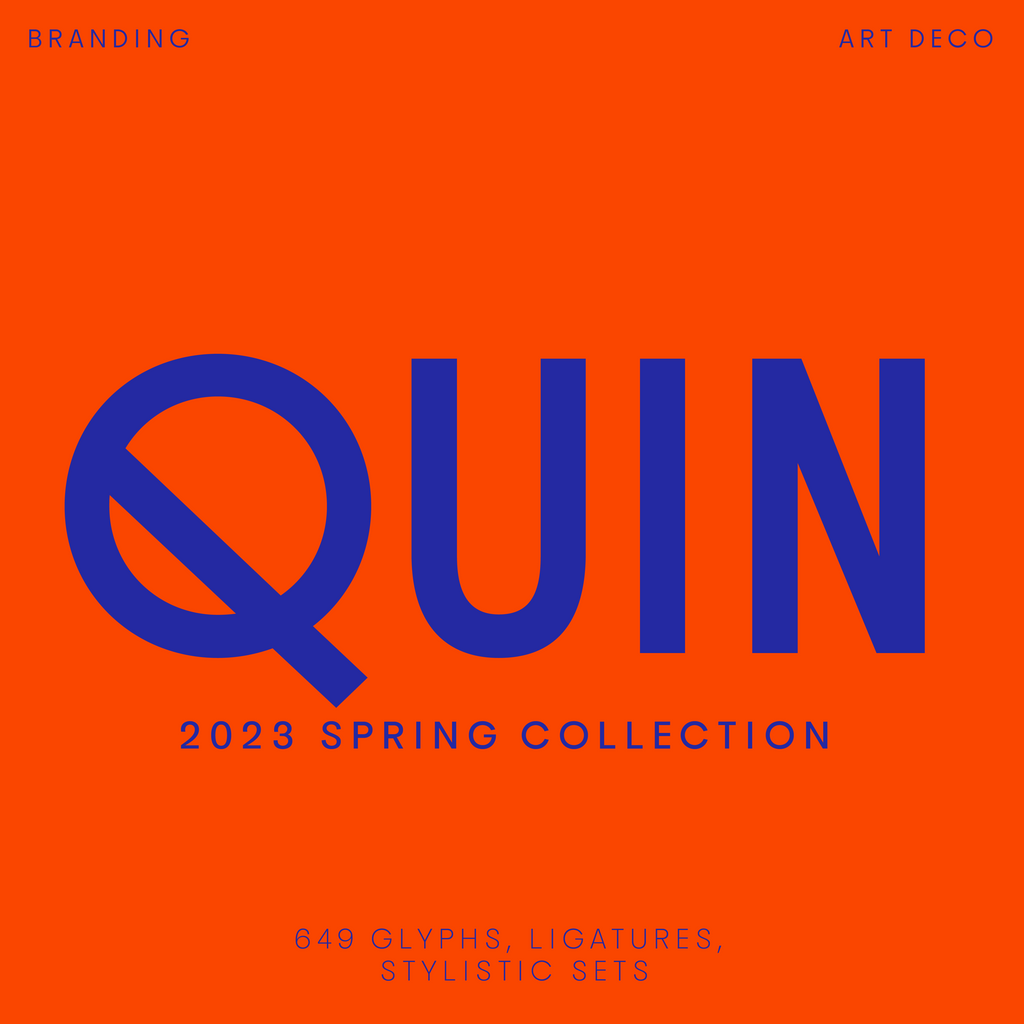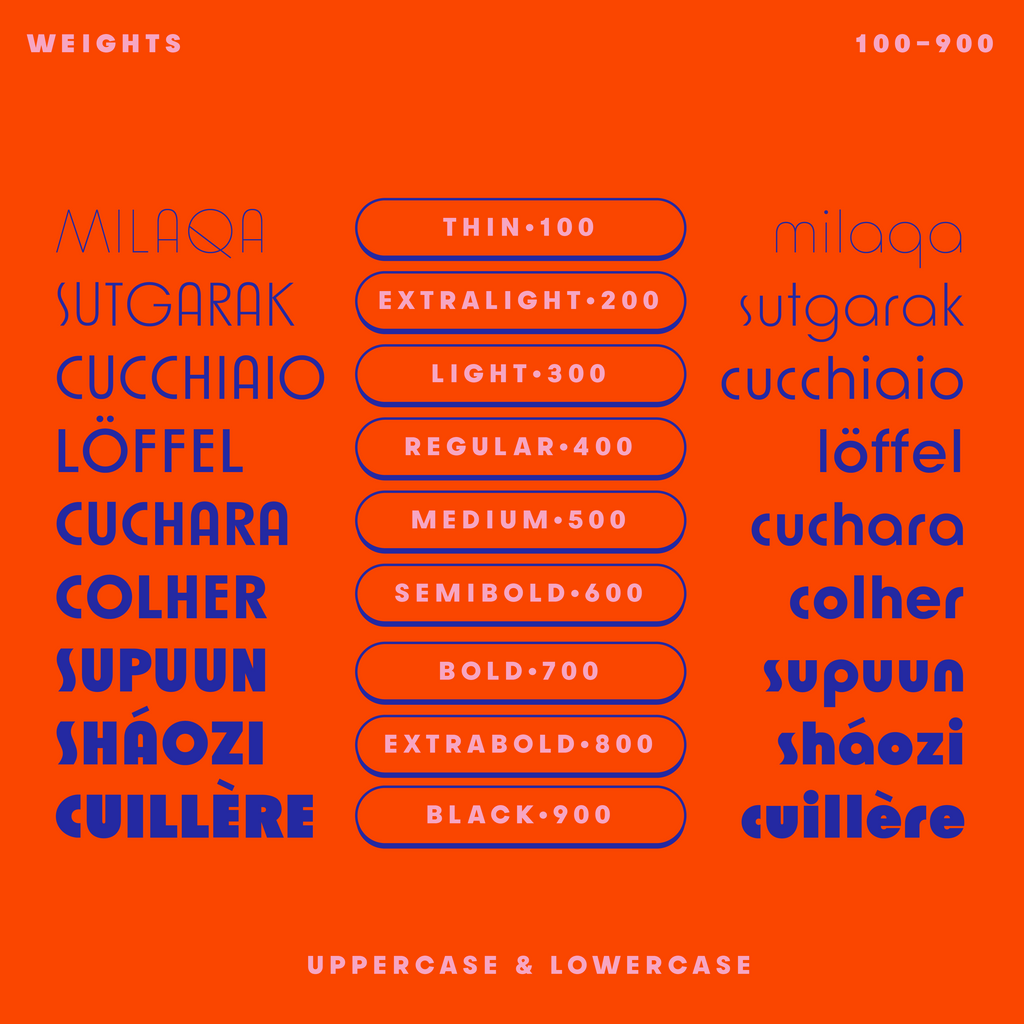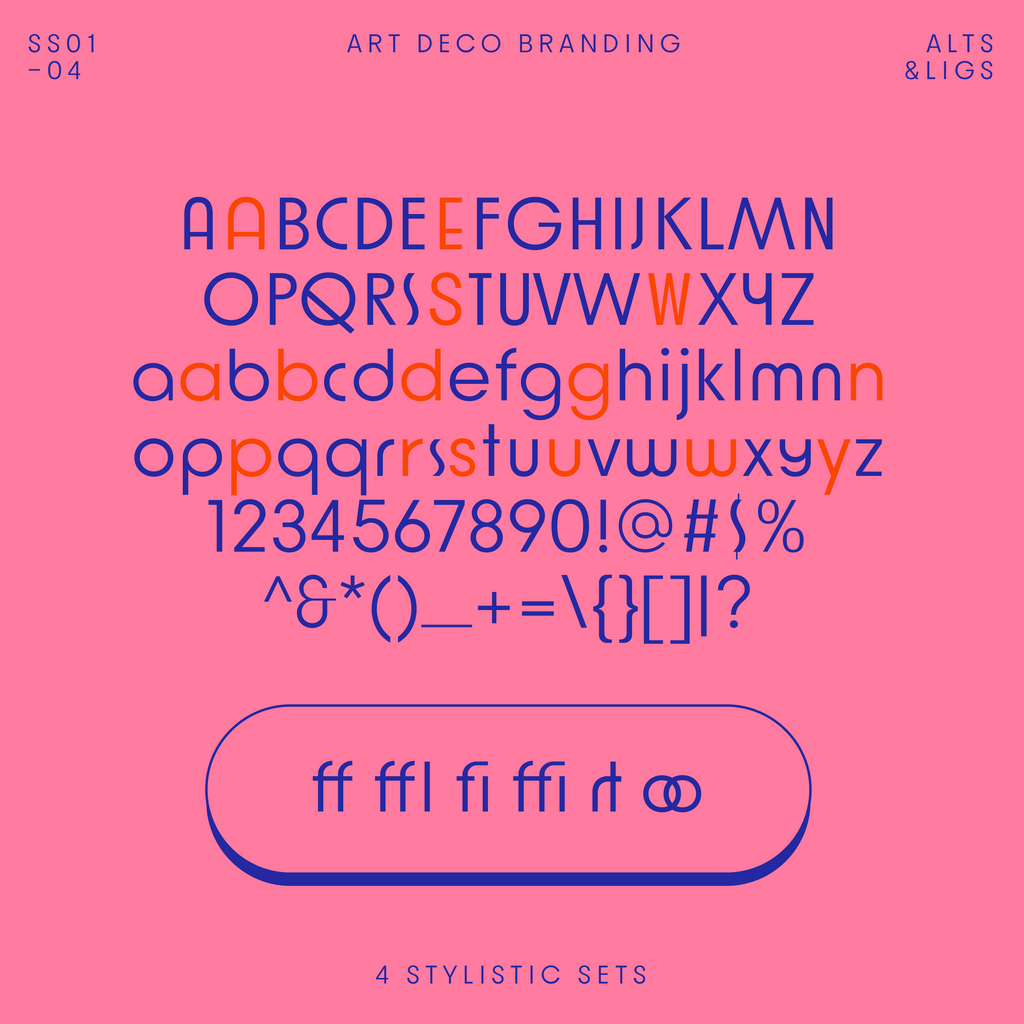
Quin: fuente sans-serif de los años 20 en estilo Art Decó
Quin es una tipografía de la década de 1920 basada en un marco geométrico. Esta fuente es ideal para marcas de restaurantes o logotipos que buscan un aspecto retro o art déco.
Quin viene en 9 tamaños de fuente, desde Thin hasta Black. (seleccione “los 9 estilos” del menú desplegable).